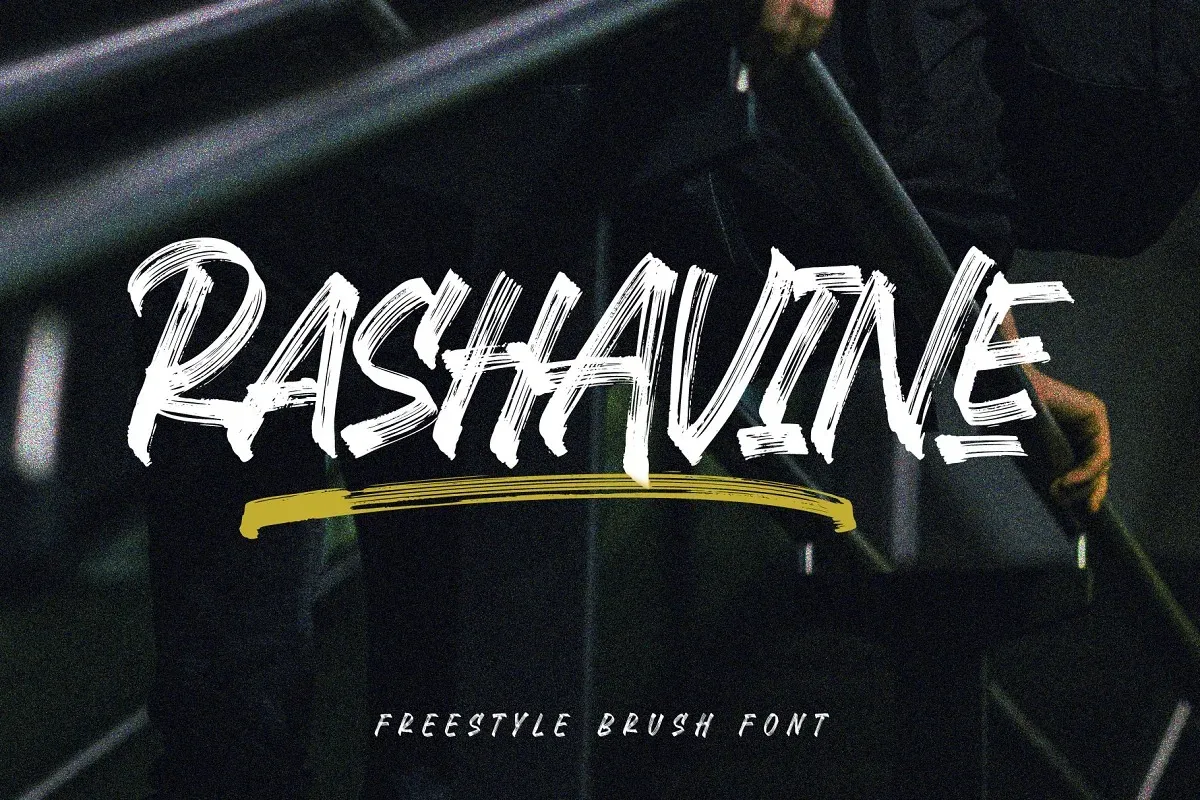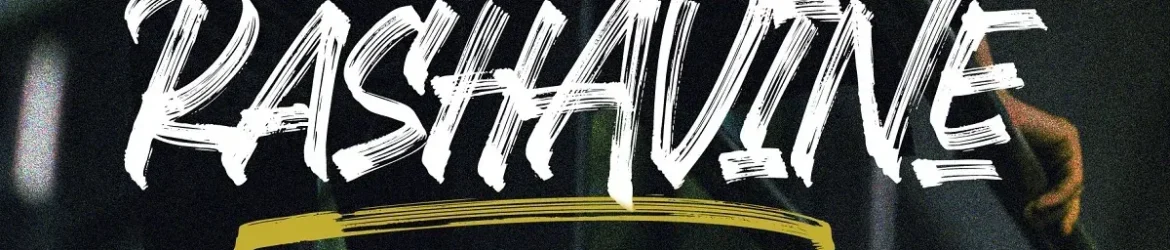
A fonte Rashavine é uma escolha perfeita para quem procura algo vibrante e criativo. Embora seja essencialmente um tipo script desenhado por Arterfak Project, ela se destaca pela sua aparência de caneta à mão com traços rúnicos, girovertes e ligaduras divertidas que adicionam uma dimensão única. Seus traços naturais criam uma sensação de energia dinâmica, estimulando os designers a criar trabalhos poderosos e rápidos. Rashavine não se limita apenas à estética: oferece alternativas de caracteres, ligaduras e swashes que permitem aplicá-la em uma ampla variedade de projetos – desde desenhos em tênis ou estampas até logos, materiais de embalagem e websites. O poder deste tipo é capaz de transformar qualquer projeto em algo animado e memorável. Não importa do que você esteja criando com Rashavine, ela tem o potencial para dar um tom vibrante e único a seu trabalho.